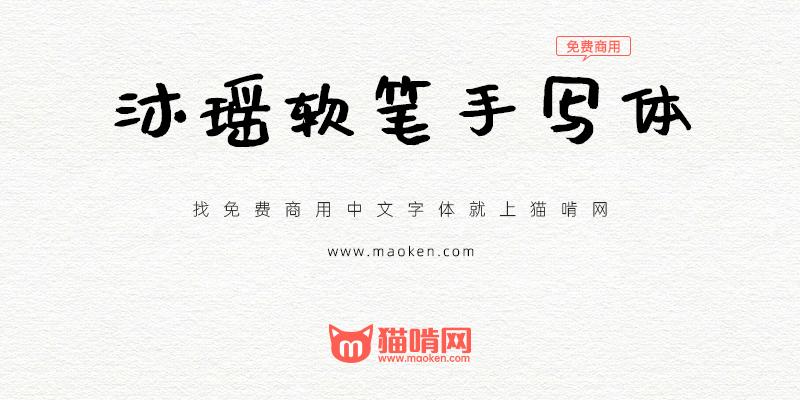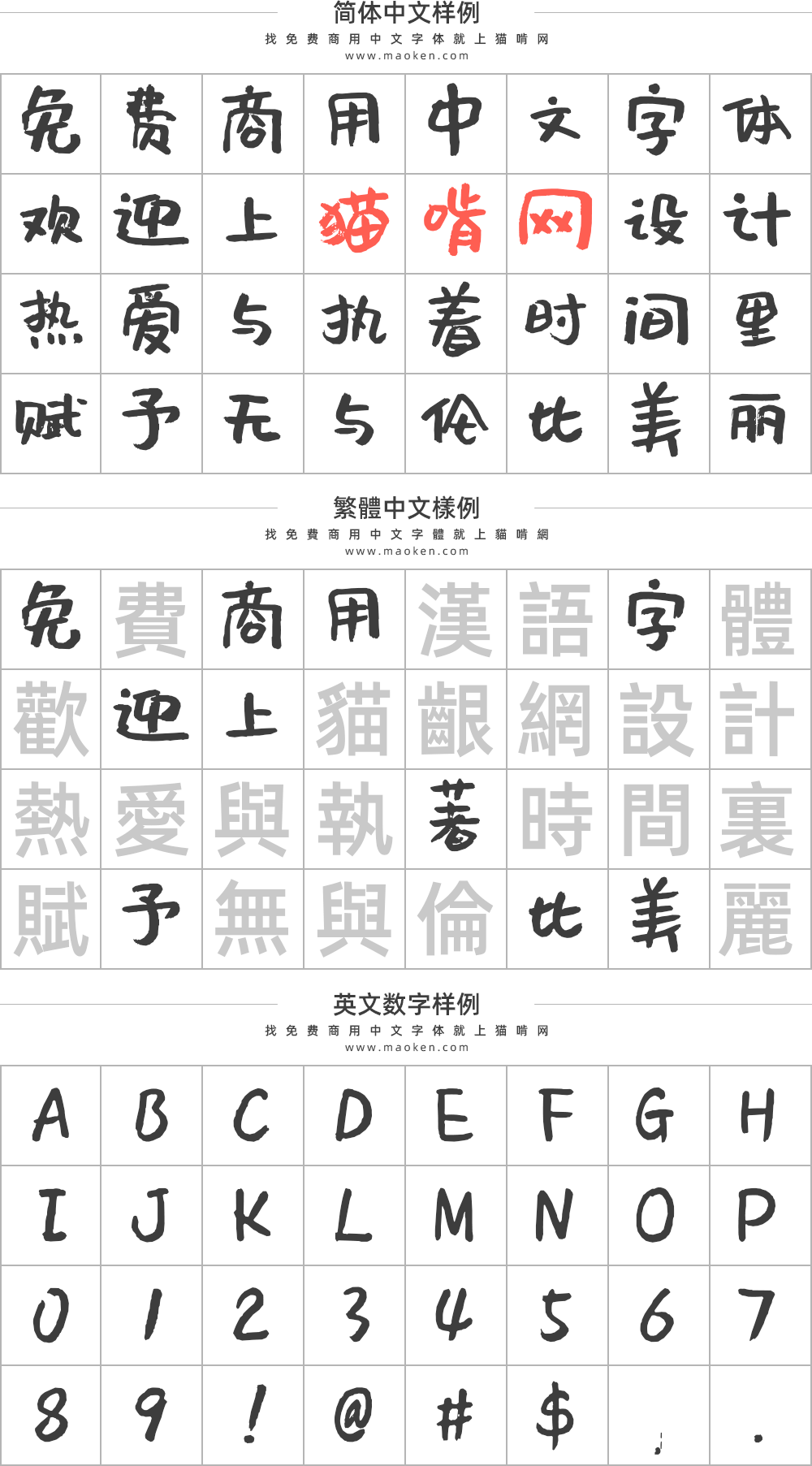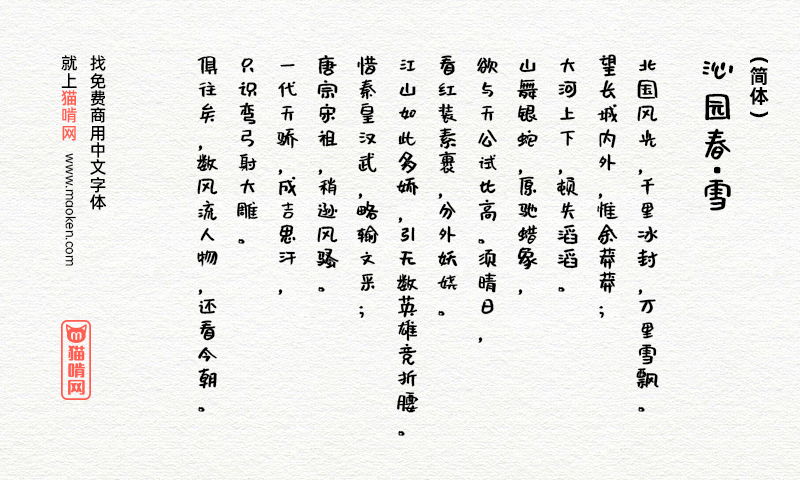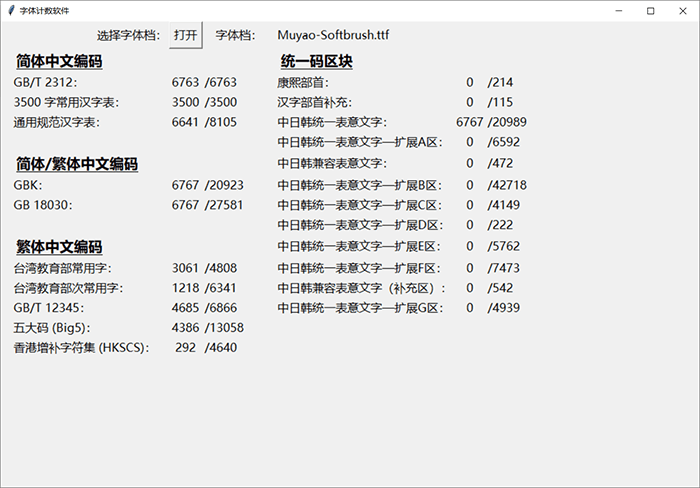
沐瑶软笔手写体:春颜秋色送给女儿和送给大家的礼物 免费商用
字体作者:春颜秋色 (中国大陆) 字体字重:1个
没有华丽的创作过程介绍,因为它的确是用笔写成,只有一个简单的故事,希望你能读一读。
我的成长经历中,没有刻意练过手写字。
不过,在手写海报方面倒是有一段经历。和现在的直接喷绘印刷不同,学生时代经常需要手写海报,经常一式多份。原本是需要用马克笔写POP字,但毕竟马克笔对于我的学生时代来说,价格很昂贵,于是大家都用排笔+广告色的方式进行创作。与传统的中文书法楷隶行草不同,这种书写方式可以把字写得较为可爱,也算是一种更加手写化的广告字体。
后来在创作漫画类作品的过程中,我发现这种字体也很适合用于休闲漫画、插画,于是在排笔书写的基础上逐渐变成了中性笔书写,并坚持了较长的时间,也逐步有了自己的书写风格。在从事平面设计的工作中,经常需要手写字,我发现楷隶行草之类的字体较多,较为休闲可爱的字体较少,好看的几款都有较为严格的版权限制,设计师使用时需要较高的门槛。
2019年5月,决定开工,匆匆在朋友圈立了FLAG,逼迫有拖延的自己去完成这个事情。
因为七月恰好是女儿周岁生日,就用女儿的名字拼音来命名,叫做“Muyao”,字母命名是方便兼容各类软件。因为是用软头毛笔写的,全名就叫做「沐瑶软笔手写体」。
我和妻子是因为写字认识的,也算是因字结缘。创作这套字体,也希望能结识更多的朋友,希望能够抛砖引玉,激发更多朋友能够创作大神级的作品。
于是,两个月,我“做”一款字体。
确切的说,是写一堆风格接近的字(GB2312标准的6763个汉字加数学英文字母和常用标点),凑成一套字体。
我知道,这也许是一件费力不讨好的事情,但是我依然认真去完成了。